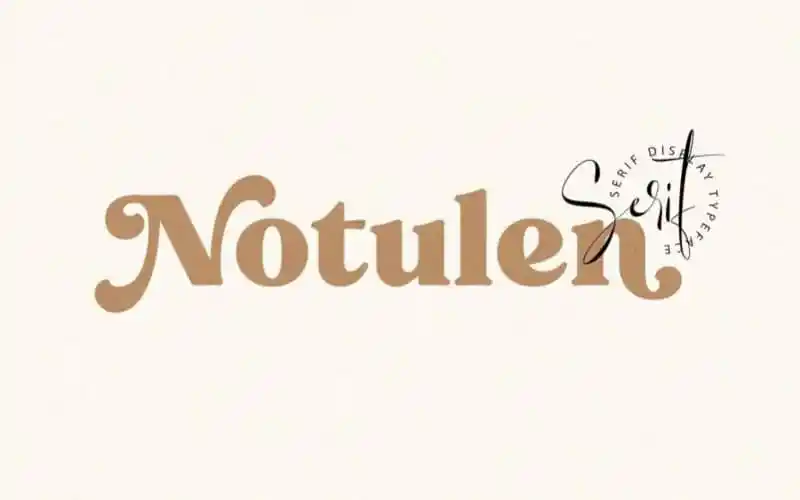
A Notulen Serif Font é uma tipografia serif para usos variados, projetada pela Siwox Studios, disponível para download gratuitamente no site 99designs. Inspirada na tipografia clássica modernizada com nuances de serif atualizadas, essa fonte se destaca por seus curtos e arredondados serifs, tornando-a legível em pontos menores. A versatilidade desta fonte não apenas permite um trabalho consistente sobre diversos projetos gráficos, mas também proporciona uma experiência mais fluida para designers, sendo ideal para aplicações como logotipos, headlines, cartazes, embalagens, camisetas, cartas de convite, assinaturas para casamentos e pintura de placas. O design modernizado do clássico torna-a uma opção atraente para quem busca um equilíbrio entre estética tradicional e contemporaneidade.